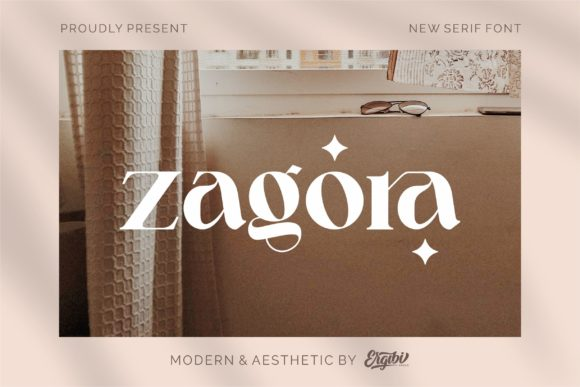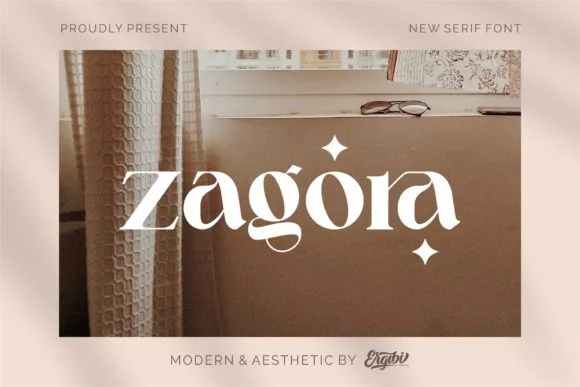
Название: Zagora Font (2021)
Zagora - это стильный, смелый и современный шрифт с засечками.
Этот шрифт имеет внушительный вид и отличается уникальной формой букв, поэтому он легко подойдет к широкому спектру творений, требующих особого штриха.